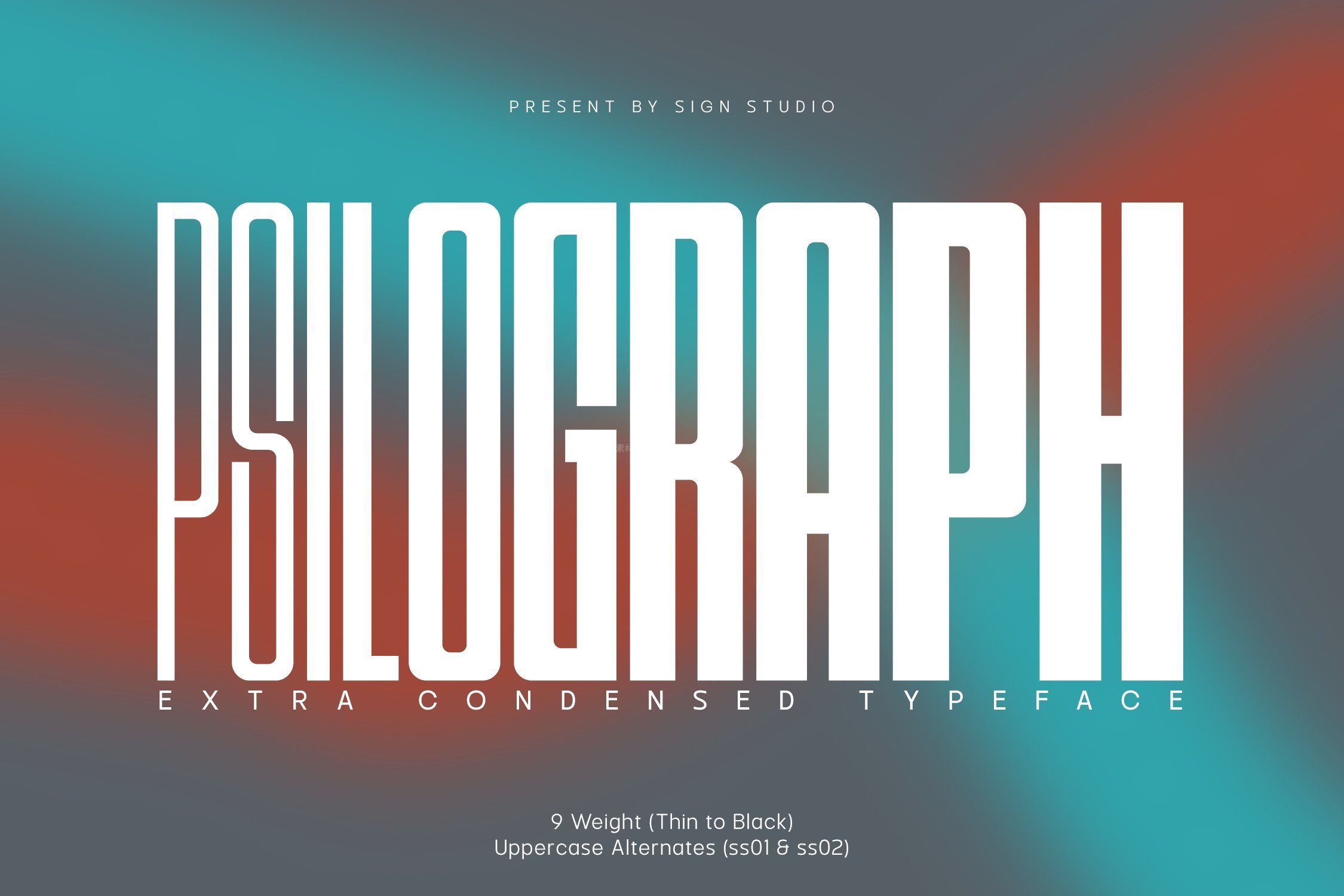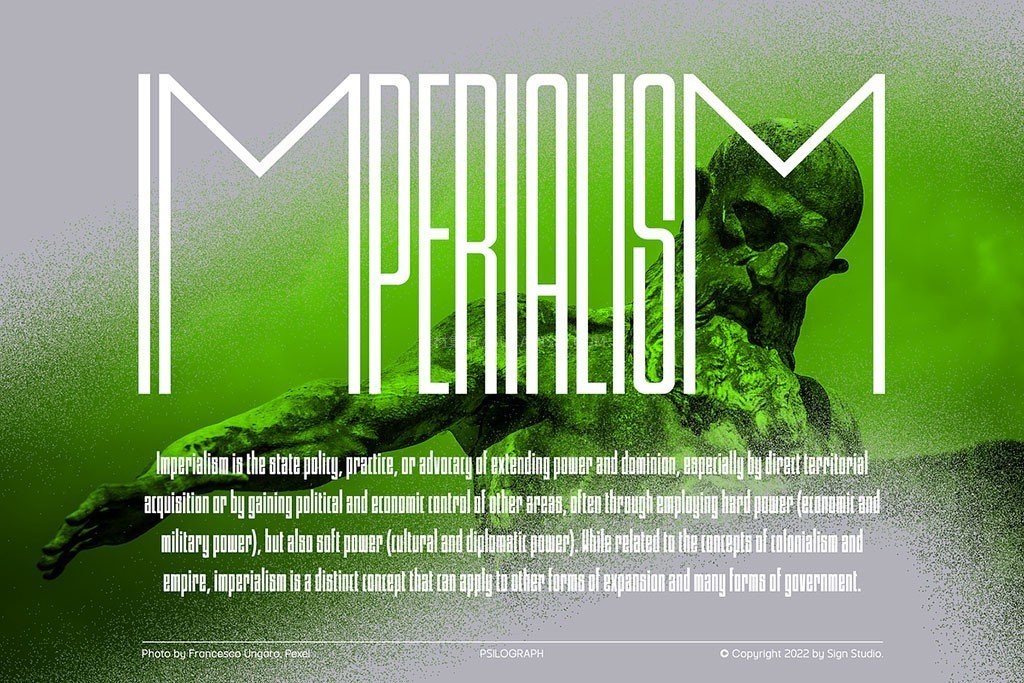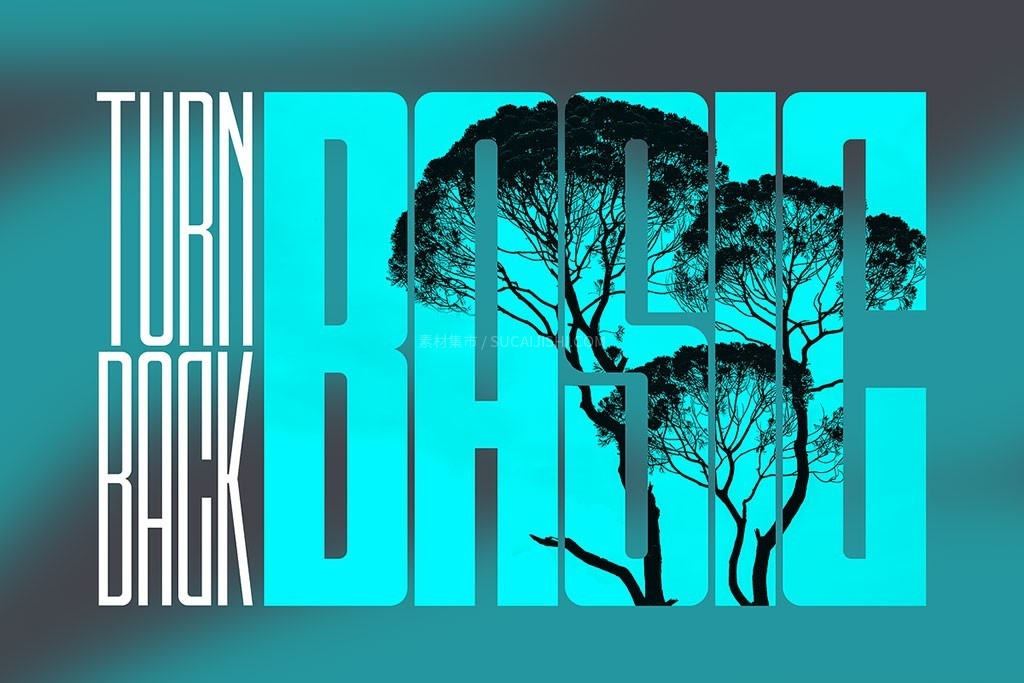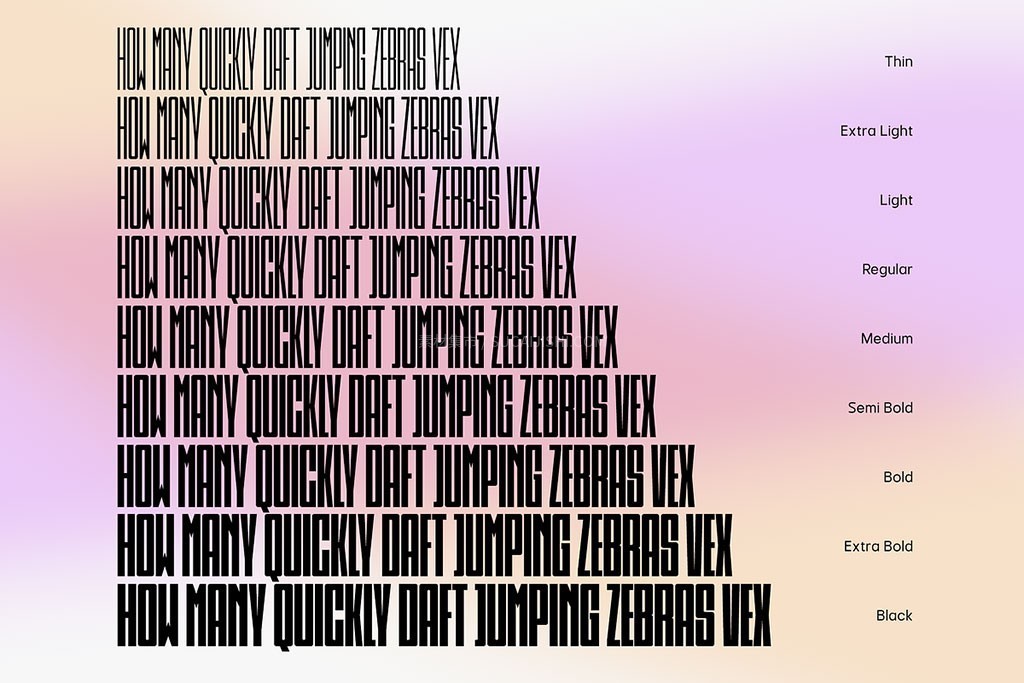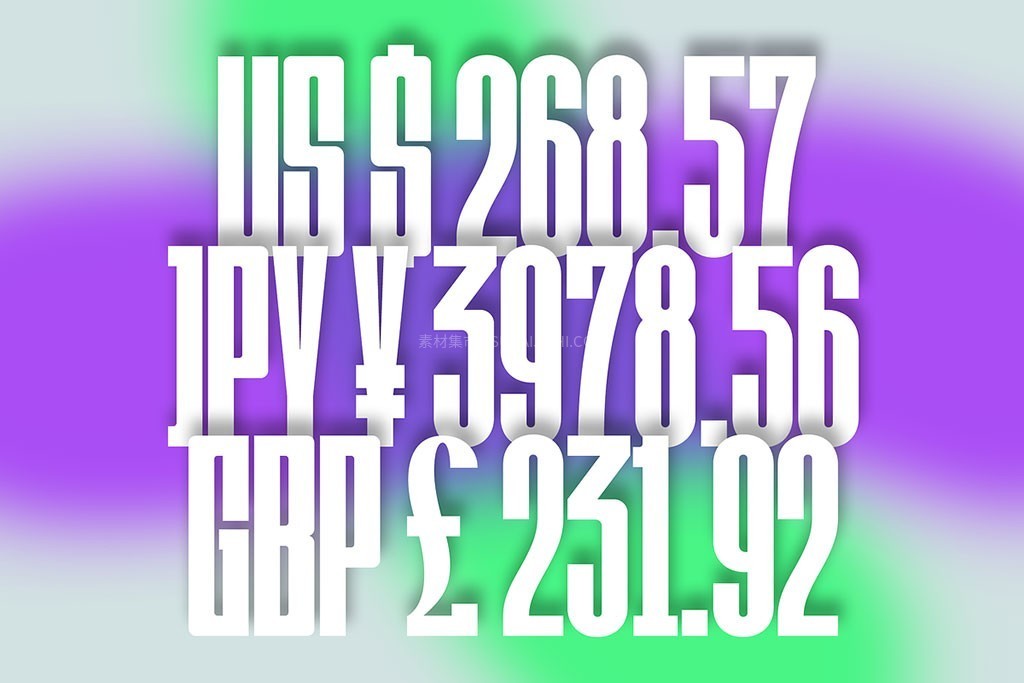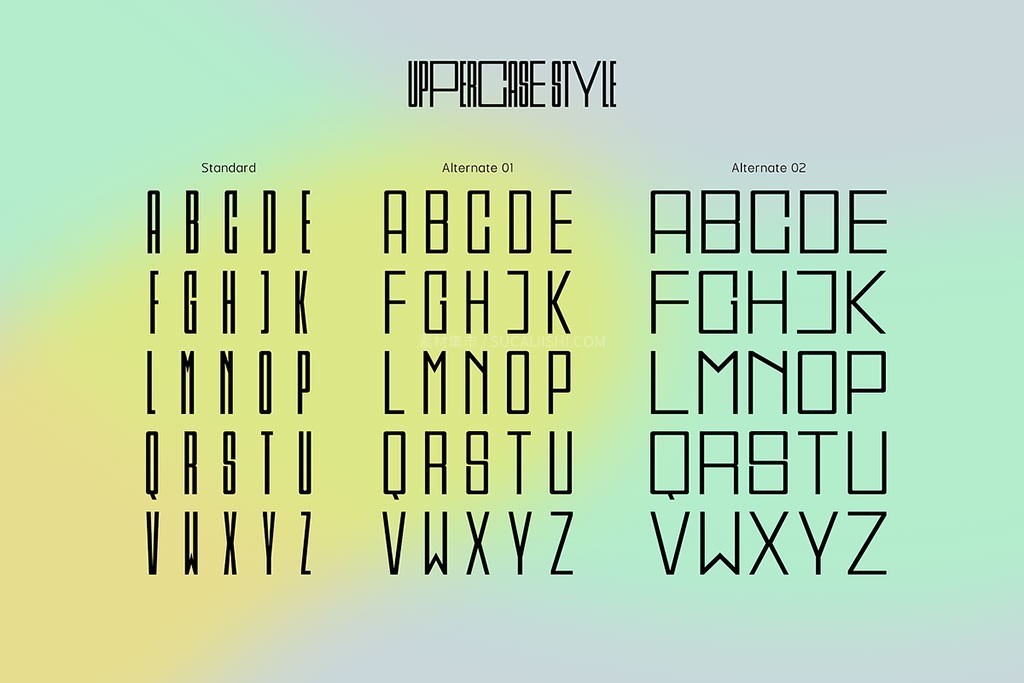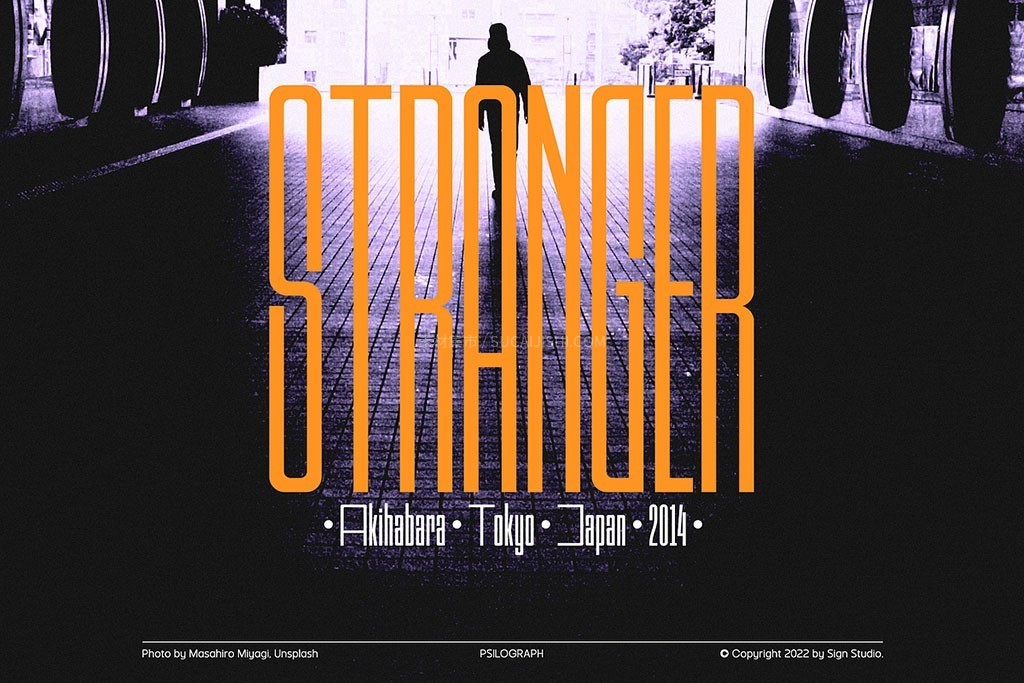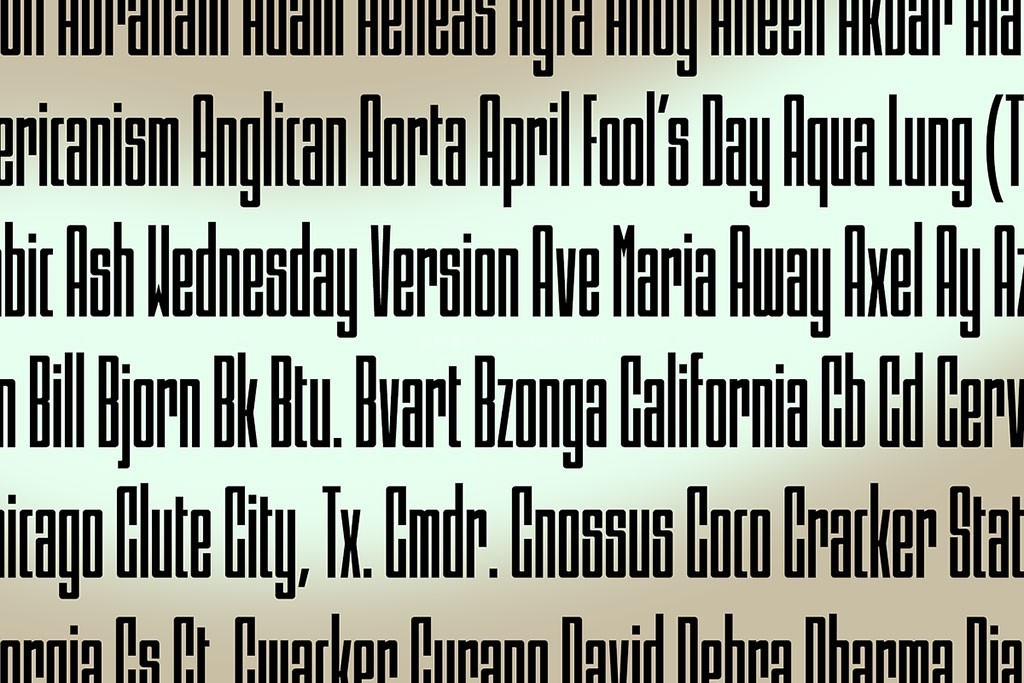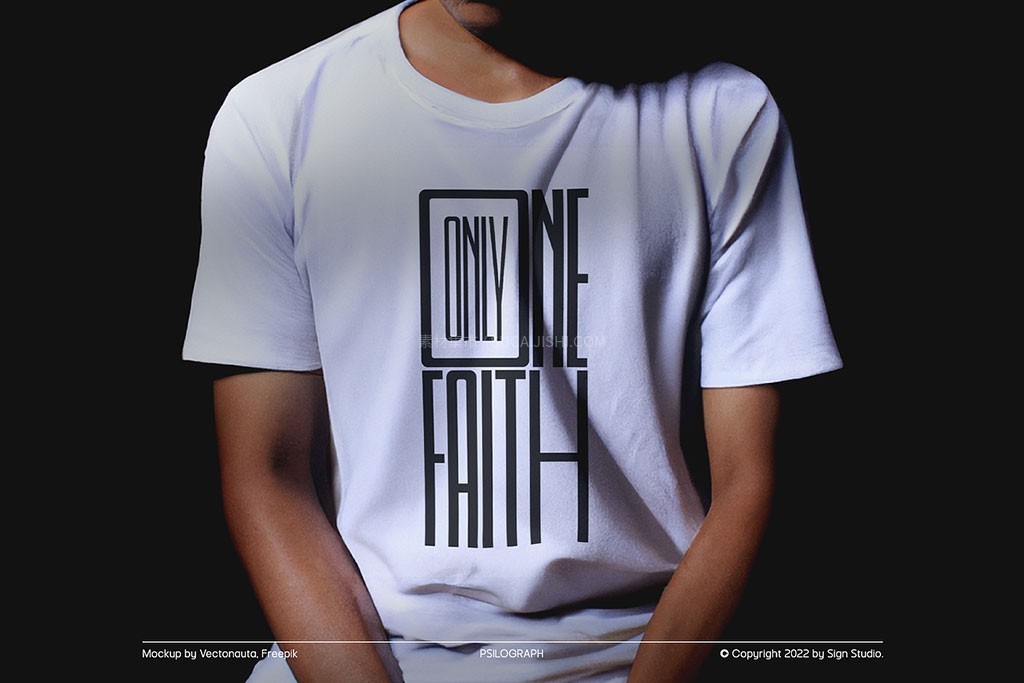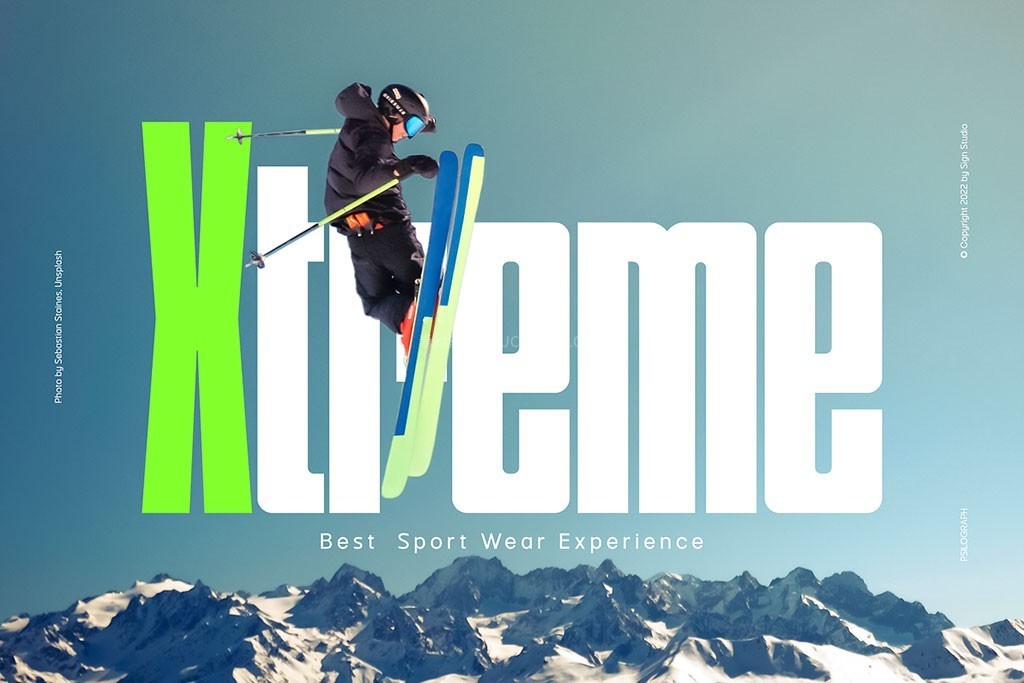
Psilograph 极简超窄体美学字体
一款极具张力的超窄体字形,内置 9 种不同粗细字重,满足各种设计场景的精细需求。完整支持常用字体格式,包含 OTF、TTF、WOFF、WOFF2,完美适配各类工作流。其修长的线条赋予了排版极佳的视觉冲击力,与简约的基础无衬线字体结合,瞬间提升整体的现代感与休闲气息。Psilograph 极简超窄体美学字体